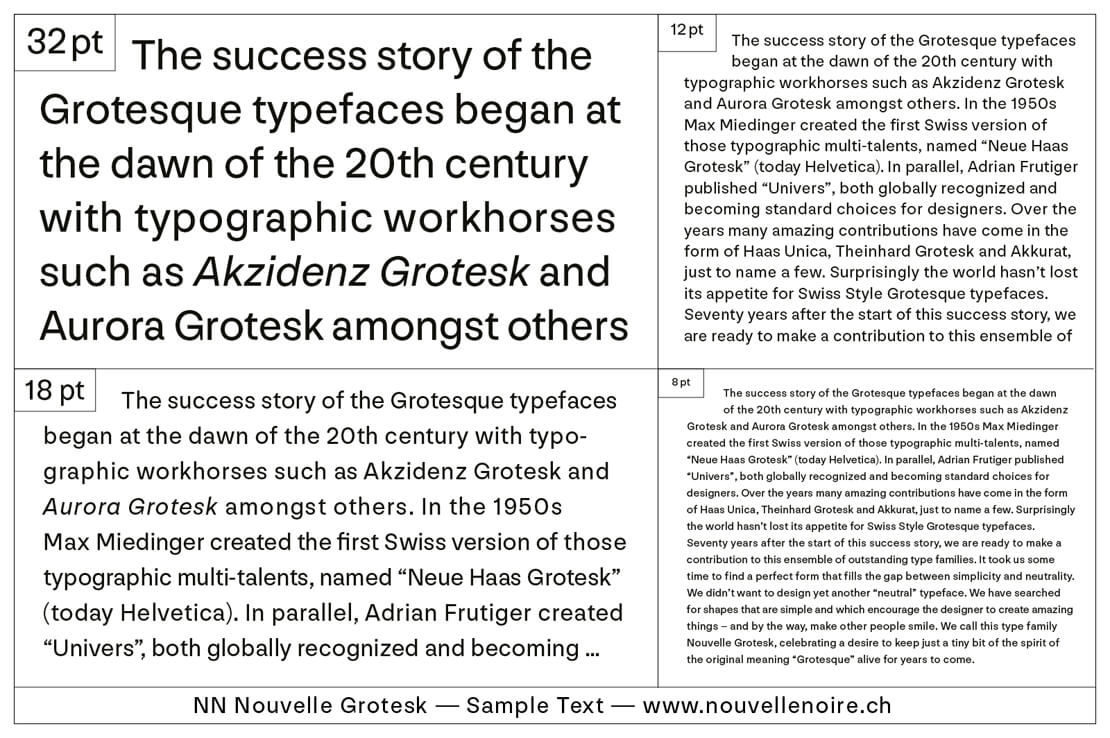
»NN Nouvelle Grotesk« von Anton Studer
Brauchen wir noch eine »weitere Helvetica«? »Ja«, meint Anton Studer und präsentiert mit »NN Nouvelle Grotesk« seine aktuelle Schriftfamilie, die bei der Schweizer Typefoundry »Nouvelle Noire« erschienen ist.
Nouvelle Grotesk Schriftart
Nouvelle Noire ist das Züricher Typdesign-Studio von Anton Studer und Clovis Vallois. Auf traditionelle Art und Weise erarbeiten die Type-Designer Schriften mit moderner Technik und möchten dabei das Bewusstsein über die Schriftgeschichte mit zukunftsweisenden Gestaltungen in Einklang bringen.
»Wir wollten nicht einfach nur eine weitere „neutrale“ Schrift entwerfen«, so Anton Studer. »Es dauerte eine Weile, bis genau die Formen gefunden werden konnten, mit denen sich die Lücke zwischen Einfachheit und Neutralität schließen lässt.«
Schnitte der Nouvelle Grotesk
»Nouvelle Grotesk« setzt daher auf einfach gestaltete Buchstaben, die mit Charme und Genauigkeit im Detail aufwarten. Die Schriftfamilie enthält die Schnitte »Thin«, »Light«, »Normal«, »Medium«, »Bold«, »Black« und »Fat«. Entsprechende kursive Varianten (sogenannte Diagonal-Schnitte) sind ebenfalls verfügbar.